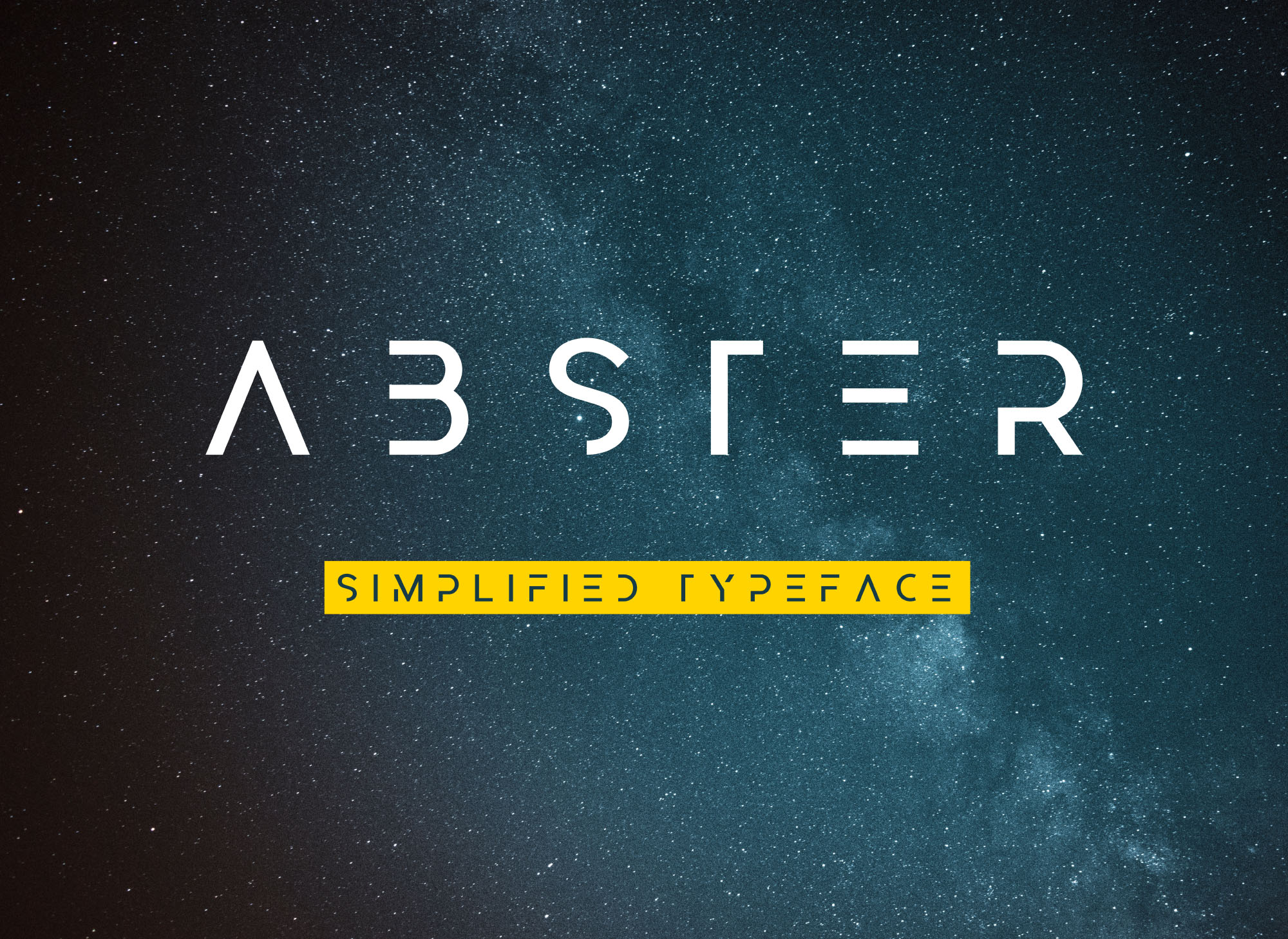
Este Abster Free Font é um exemplar perfeito da famosa categoria de fontes geométricas. Ela é uma tipografia abstrata simplificada construída sobre uma grade geométrica, com um estilo elegante e moderno. A equipe que criou este recurso teve cuidado em reduzir o tamanho da fonte apenas o suficiente para torná-la legível e legível. Essa tipografia é incrivelmente adequada para uso em cabeçalhos, cartazes e designs de marca. Este font é uma escolha ideal para quem deseja adicionar um toque geométrico e moderno a seus projetos visuais.